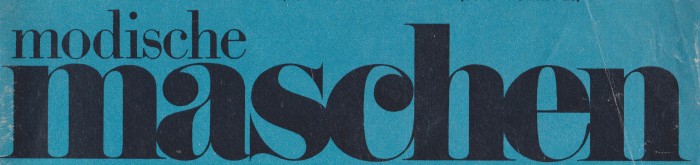
kann mir irgendwer sagen welche schrift das ist? bei whatfontis und what the font hab ich nichts gefunden.. das ist der titel eines ddr strickmagazins.
das Wort »modische« würde ich für eine Bodoni halten, das Wort »Maschen« ist irgendeine an Bodoni/Didot/Walbaum orientierte Displayschrift, es könnte die »Sahara Bodoni« sein.
(Um die Schrift bei Whatthefont zu suchen, müsste man den Kontrast so erhöhen, dass der Hintergrund weiß wird, die Buchstaben einzeln ausschneiden und dann mit Abstand zueinander in die Suchmaschine füttern.)
Zu der Zeit wurden Logos meist gezeichnet, nicht gesetzt. Worum geht es dir? Willst du das Logo nachsetzen? Oder geht es nur um die Information?
Generell wäre das stilistische Stichwort Bodoni. Da gibt es unterschiedlichste Digitalisierungen.
Oh, da wart ihr schneller ;-) Hab mir auch die Mühe gemacht, was ähnliches bei MyFonts zu suchen, aber das Feld ist weit im Bodoni/Didone Raum …
(PS: wenn es sich um eine DDR-Zeitschrift handelt, kommt man mit den zeitgenössischen Methoden vielleicht auch nicht wirklich weiter, wenn es um exakte Information geht)